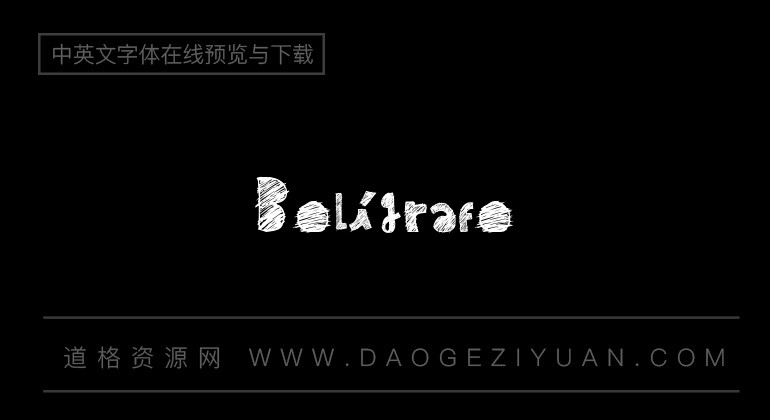
Bolígrafo是一种现代风格的手写字体,源自西班牙语单词“bolígrafo”,意为“圆珠笔”。它具有非常明显的手写感,其笔画粗细变化明显,字母之间的间隔较大,使其易于阅读和识别。 Bolígrafo字体适用于各种用途,例如海报设计、品牌标识、书籍封面、卡片设计等。由于其现代且率性的风格,它经常用于年轻和创新的品牌标识。 总之,Bolígrafo字体是一种受欢迎的、现代化的手写字体,适合各种用途。内容介绍
Bolígrafo是一款非常不错的手写艺术字体,具有很好的视觉感,适合于文化类的宣传设计、商业类品牌的广告和产品包装设计以及个性化文字排版等较多场景。